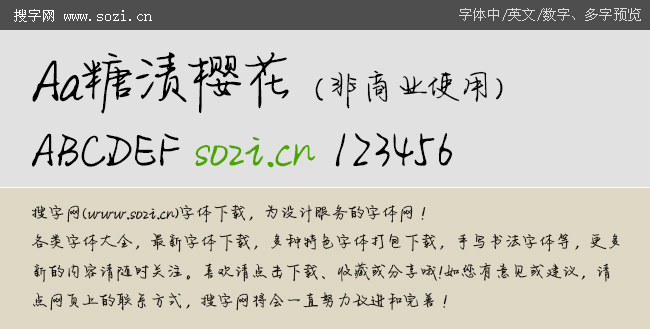
Aa糖漬櫻花
搜字網(wǎng)給大家提供一款A(yù)a糖漬櫻花(非商業(yè)使用)中文字體下載,Aa糖漬櫻花是一款硬筆手寫書法字體,,該字體書寫流暢,瀟灑大方,結(jié)構(gòu)比較工整,具有很好的視覺感。適合應(yīng)用于藝術(shù)設(shè)計(jì)、平面宣傳設(shè)計(jì)、網(wǎng)頁設(shè)計(jì)、海報(bào)設(shè)計(jì)等應(yīng)用(此字體為個(gè)人非商用版,商用可以聯(lián)系QQ:1006760504)。